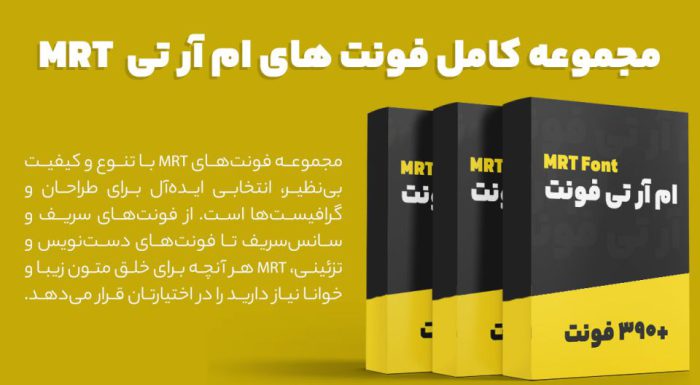
مجموعه کامل فونت های MRT فارسی (+390 فونت)
مجموعه کامل فونت های MRT فارسی: بیش از ۳۹۰ قلم متنوع
مجموعه فونت های MRT (مخفف احتمالی “مرکز رایانه تک” یا نامی مشابه)، یک گنجینه عظیم از تایپ فیس های فارسی است که برای پاسخگویی به نیازهای متنوع طراحان گرافیک، ناشران، کاربران نرم افزارهای اداری و علاقه مندان به زبان فارسی گردآوری شده است. این مجموعه با بیش از ۳۹۰ فونت، یکی از کامل ترین آرشیوهای فونت MRT است که شامل فونت های جدید و قدیم منتشر شده توسط این سازنده می شود.
ویژگی های اصلی مجموعه:
- جامعیت بالا: این پکیج تمامی فونت های MRT را در بر می گیرد، از قلم های ساده و خوانا گرفته تا فونت های فانتزی، تزئینی، و خطوط الهام گرفته از خوشنویسی.
- کاربرد چندمنظوره: فونت های MRT برای استفاده در طیف وسیعی از نرم افزارهای دسکتاپ طراحی شده اند:
- نرم افزارهای آفیس (ورد، اکسل، پاورپوینت): برای تولید اسناد متنی، گزارش ها و ارائه های حرفه ای.
- نرم افزارهای گرافیکی (فتوشاپ، ایلاستریتور، کورل دراو): برای طراحی پوستر، بنر، لوگو، کارت ویزیت و انواع طرح های گرافیکی خلاقانه.
- نرم افزارهای مهندسی (اتوکد): برای نوشتن توضیحات و متون در نقشه ها و طرح های فنی.
- افزایش زیبایی بصری: استفاده از این فونت ها به طرح های شما جلوه ای زیبا و حرفه ای می بخشد و به طراحان امکان می دهد تا با انتخاب فونت مناسب، پیام خود را به بهترین شکل ممکن منتقل کنند.
نمونه ای از فونت های موجود در مجموعه (برخی از بیش از ۳۹۰ فونت):
دانلود- MRT Abasan Regular: یک قلم ساده و کلاسیک.
- MRT Advertising (Bold, Extra Bold, Light, Medium): برای تبلیغات و عناوین با وزن های مختلف.
- MRT AridiKoufi Regular و MRT AridiNaskh (Black, Bold, Plain): فونت های الهام گرفته از خطوط کوفی و نسخ.
- MRT Beirut (Bold, Heading Bold, Light, Lt X3, Md): مناسب برای عناوین و متون.
- MRT Diwani (3D Shadow, Collage, Decor, Normal, Outline): الهام گرفته از خط دیوانی با سبک های مختلف.
- MRT Elegant (Bold, Light, Medium): برای طراحی های شیک و ظریف.
- MRT Fantezy (Cut, Flage, Regular, Wave): فونت های فانتزی و خلاقانه.
- MRT Farah (Bold, Italic, Light, Medium, Outline): فونت های متنوع برای کاربردهای مختلف.
- MRT King (1 Bold, 2 Regular): قلم های سلطنتی و رسمی.
- MRT Nazila (3D Shadow, Bold, College, Cow, Gol): با سبک های تزئینی و فانتزی.
- MRT Naskh Titr (Bold, Outline, Shadow): برای تیترهای نسخ.
- MRT Poster (از 1 تا 18 و Regular): مجموعه ای از فونت های مناسب پوستر و بنرهای بزرگ.
- MRT Shafigh (Bold, Mangle, Outline, Regular, Shade, Stripe): فونت با تنوع بالا در سبک.
- MRT Titr (3D, Cactus, Collage, Cow, Outline, Particle, Stripe): برای تیترها با افکت های متنوع.
- MRT Typographer (Bold, Book, Heavy): برای کاربردهای تایپوگرافیک.
- MRT Unique (Bold, Expanded, Light): فونت های خاص و متمایز.
- MRT Yalda Bold: فونت زیبا و پرکاربرد.
مجموعه فونت های MRT به دلیل تنوع بسیار بالا در سبک و وزن، برای طیف وسیعی از کاربردها در حوزه های مختلف طراحی گرافیک و نشر بسیار کارآمد است.
کاربردهای اصلی:
- طراحی گرافیک حرفه ای: این مجموعه برای طراحان گرافیک که نیاز به فونت های متنوع برای لوگو، پوستر، بنر، کارت ویزیت، و مواد تبلیغاتی دارند، ایده آل است. فونت های فانتزی، تزئینی و خاص در این مجموعه، امکان خلاقیت بی حد و حصر را فراهم می آورد.
- نشر و چاپ: برای طراحی کتاب، مجلات، روزنامه ها، و بروشورها، فونت های ساده و خوانا مانند MRT Abasan Regular یا MRT Naskhi Regular بسیار مناسب هستند، در حالی که فونت های تیتر (مانند MRT Titr یا MRT Poster) برای عناوین و سرفصل ها به کار می روند.